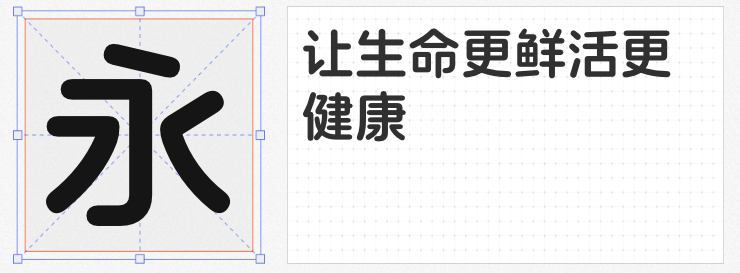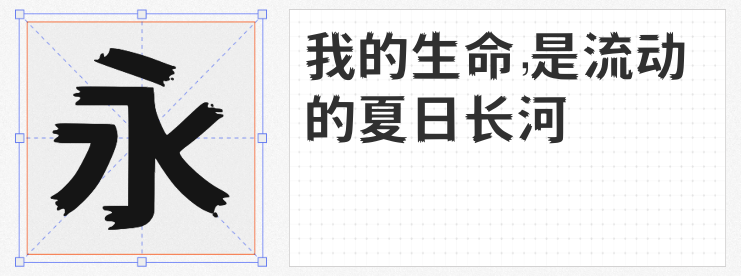
在社交媒体视觉竞争白热化的当下,一款契合主题、风格鲜明的字体,往往能成为封面设计的点睛之笔。以下四款免费商用字体,凭借独特的设计语言与广泛的适配性,为社交媒体封面注入个性魅力,助力品牌快速抢占用户注意力。
这款字体以“亲和、稳重、简约”为核心气质,通过计算机字库技术创新,首次实现汉字字符与盲文的串联——每个汉字右下角均嵌入了对应的盲文点字,既保留了现代字体的简洁感,又赋予其无障碍传播的社会价值。其笔画粗细均匀,结构端庄,适用于医疗健康、公益科普类社交媒体封面,既能传递专业可信的形象,又能通过盲文细节彰显品牌的人文温度。
作为思源宋体的反向插值衍生字体,这款特粗体完美延续了思源家族的东方韵味,同时以更强烈的视觉冲击力适配标题场景。其笔画粗壮有力,中宫开阔,与思源宋体其他字重搭配使用时,能形成层次分明的排版效果。无论是传统文化、教育学术类账号的封面标题,还是需要强调信息层级的图文内容,这款字体都能以“和谐而突出”的姿态,提升整体设计质感。
这款字体将中国古建筑的“飞檐”特征融入笔画设计,大部分笔画末端以尖角外挑,结构转角采用非正圆倒角,既保留了黑体的简洁性,又增添了人文无衬线的设计感。其复古而不失现代的视觉风格,尤其适合国风文化、历史解读、创意设计类社交媒体封面,能通过飞檐般的笔画细节,瞬间唤醒受众对传统文化的联想。
以黑体为蓝本,这款字体通过撕裂的锯齿状边缘与稳健的笔画结构,塑造出“刺猬”般的双重性格——既有锋芒毕露的视觉冲击,又蕴含柔软坚韧的内在力量。其设计语言与《哪吒》中魔丸哪吒的形象不谋而合,适合游戏电竞、潮流文化、青年社群类社交媒体封面,能以叛逆不羁的字体风格,精准触达年轻受众的审美偏好。
这四款免费商用字体,覆盖了科技、文化、潮流、公益等多重领域,既能满足社交媒体封面对视觉冲击力的需求,又能通过细节设计传递品牌内核。选择它们,让你的封面设计在信息洪流中脱颖而出!